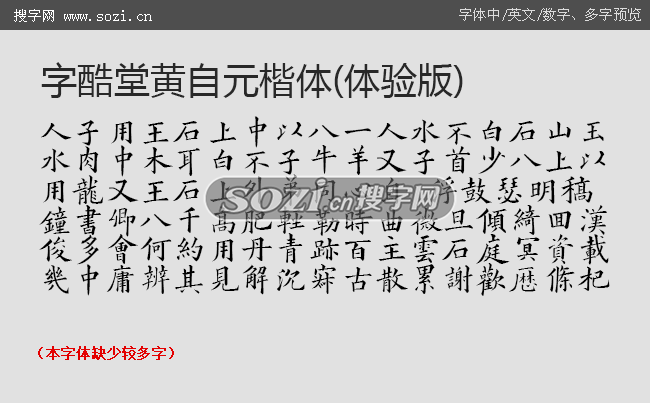
字酷堂黃自元楷體(體驗版)
搜字網(wǎng)提供一款字酷堂黃自元楷體(體驗版)手寫中文書法字體下載,字酷堂黃自元楷體(體驗版)是一款非常漂亮的手寫字體,字體極具藝術(shù)風(fēng)格,每筆每畫都給人一種飄逸灑脫的感覺,整體效果非常出色,能夠應(yīng)用于平面設(shè)計、名片設(shè)計、廣告創(chuàng)意、印刷等場合應(yīng)用。